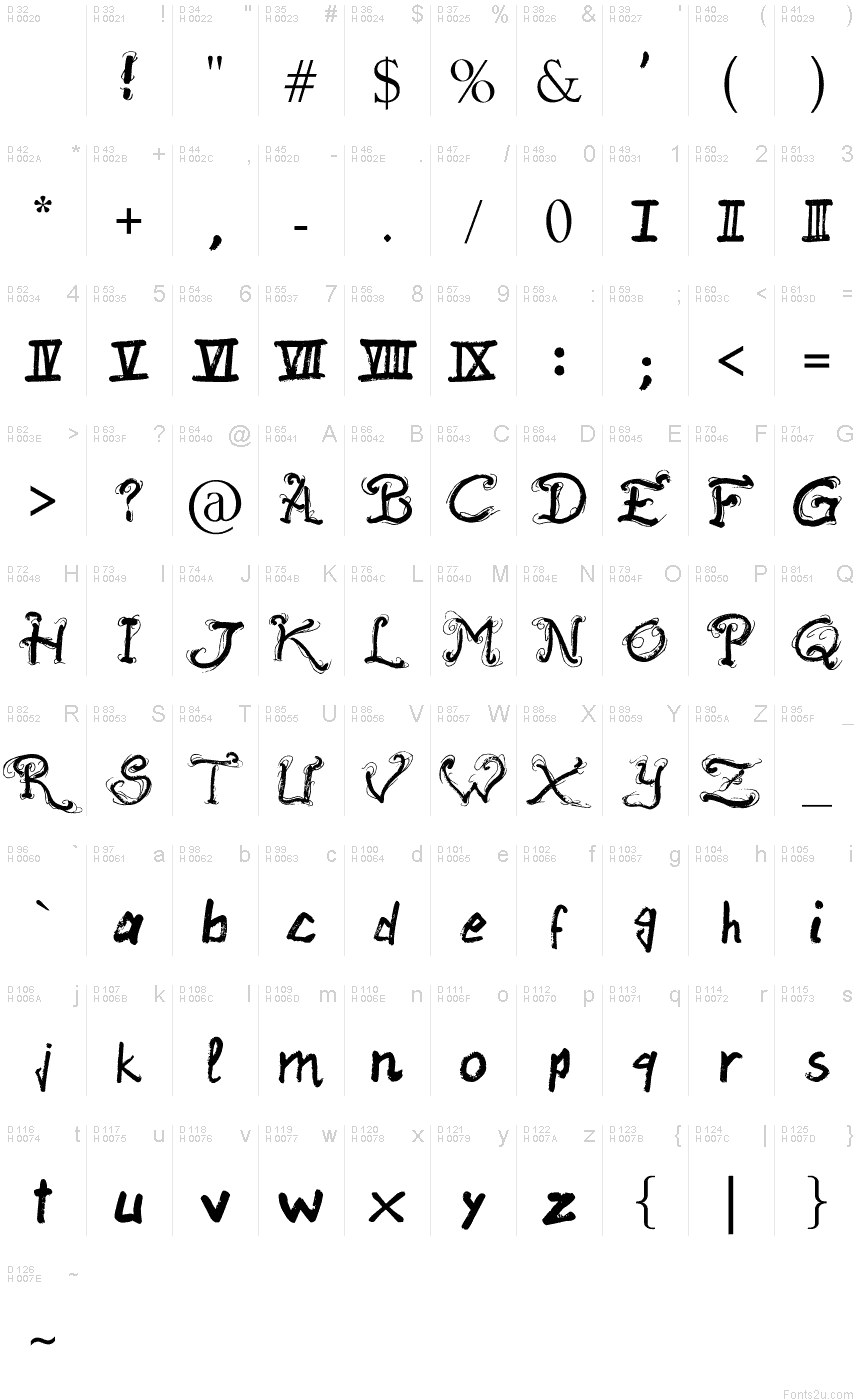
Raslani Ancient Script
Raslani Ancient Script od Le Raslani to darmowy, kaligraficzny krój pisma o klimacie starych, wytartych atramentem dokumentów. Litery łączą w sobie wyraziste zawijasy z surowymi, nierównymi krawędziami, dzięki czemu całość przypomina bardziej stary rękopis lub malowane pędzlem napisy niż sztywną, formalną kaligrafię.
Sprawdzi się wszędzie tam, gdzie potrzebujesz historycznego wydźwięku z nutą surowości: na okładkach książek, plakatach, oprawach muzycznych, grafikach eventowych czy w krótkich hasłach brandingowych. Jako darmowy font, doskonale nadaje się też do plansz tytułowych, cytatów czy inicjałów – długie loki i przetarte kreski nadają nawet pojedynczym literom charakter znaleziska z dawnego archiwum.